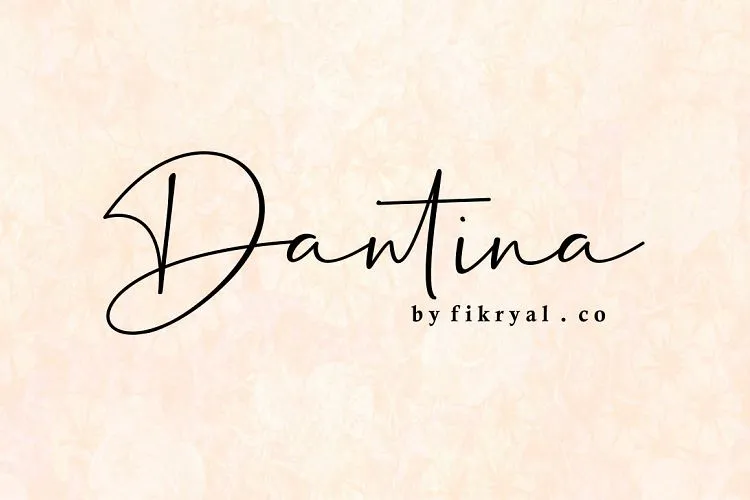
Dantina Handwritten Font – Download Grátis
A Dantina Font é uma abordagem única no mundo das fuentes script, combinando estilos manuscritos vintage, retro e moderno para criar nuances exóticas nos caracteres. Esta fonte perfeita para sua necessidade inclui logotipos, marcações, produtos e embalagens, revistas, design web, anúncios, bandas, panfletos, títulos e muito mais. A Dantina não só apresenta alternativas completas e uma ligatura de alta beleza para garantir um acabamento elegante e atraente para seus produtos, mas também oferece suporte multilíngue. Para quem busca algo único que combine elementos modernos com estilos antigos, a Dantina Font é a escolha ideal. Suas alternativas completas e ligatura única proporcionam ao seu produto uma aparência elegante e atraente, fazendo dele um diferencial no mercado. Seja para design web ou impressão em massa, esta fonte perfeita atende todas as suas necessidades de criatividade e elegância.